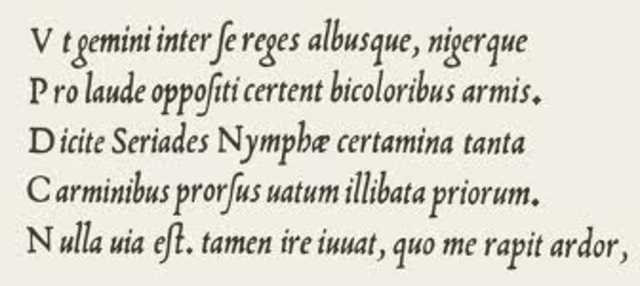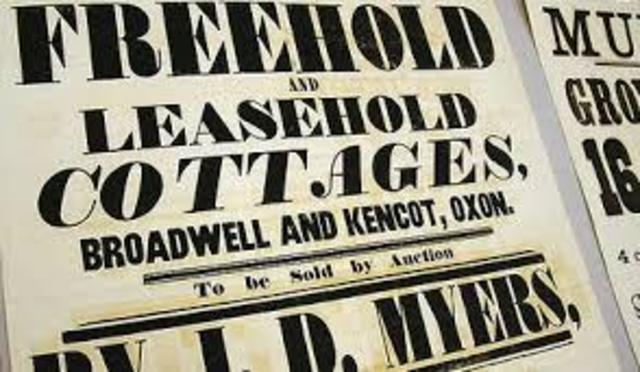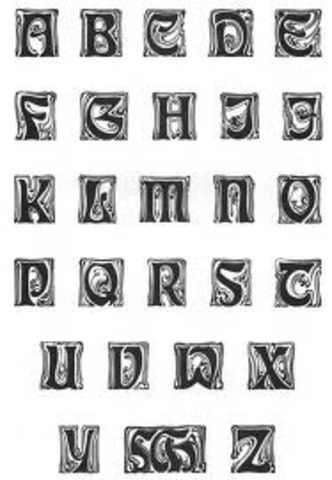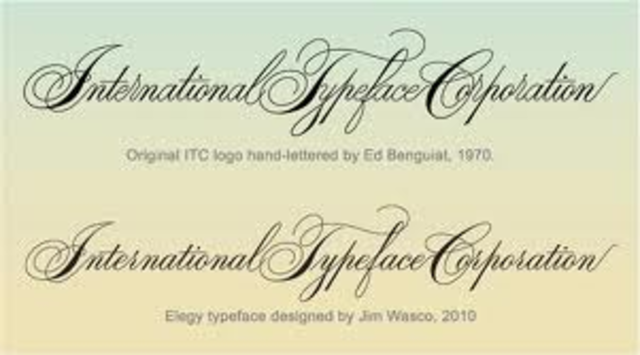
Johann Gensfleish Zum.
Desarrollo una tecnica para la elaboracion de diferentes moldes que se utilizarian para imprimir letras individuales.
Lugar: Alemania -
Introdujo la imprenta en Lyon, Francia.
imprimió el libro Le Mirover de la Rèdemption, utilizando tipos y grabados en madera importados de Basilea. -
Creó el primer manual de escritura del s. xvi; en donde publicó un segundo manual realiza do con bloques de madera, cuyas páginas estaban impre sas con tipos itá licos que él diseñó.
Fue el primer fundidor de tipos que trabajó de
forma independiente; gracias a sus caracteres romanos, los impresores franceses publicaron libros con gran legibilidad y belleza. -
Se hacen populares los libros de bolsillos. Y tambien fueron escritos libros en ingles.
inició la estandarización del tamaño de los tipos al publicar su Primera Tabla de Proporciones y abrió su propia fundición en París en 1739 y publicó su libro de modelos llamado Modèles des caractéres de l´imprimerie et desautres choses nécessaires au dit art, donde muestra sus 4600 caracteres que diseñó y talló en seis años. Dio a los impresores del Rococó un sistema completo de diseño (romanas, itálicas, plumilla, estilo decorativo, líneas y ornamentos) con medidas estandarizas.
Joseph Jackson y Thomas Cottrell:
in novadores: Joseph Jackson y Thomas Cottrell fueron prolífi cos diseñadores de letras y fundidores. Al parecer Cottrell comenzó a fundir en moldes de arena toscas letras negritas. Otros fundidores adoptaron la idea de letras más grandes y gruesas y, gradualmente, los tipos se hicieron más pesados. -
Se realizó en 2 espesores distintos y el recuerdo de la plumilla medieval se ve refl ejado en los rasgos principales de las letras, no es recomendable para cuerpos de texto.
Hermann Zapf:
Comenzo a desplazar a los caracteres de metal fundido. Lo más sobresaliente de este periodo fue la consolidación del dominio del estilo internacional suizo en el mundo de la composición; el estilo internacional de la escuela suiza se basa en el uso de una retícula para los diseños, en el uso casi excluyente de los tipos grotescos y en las composiciones asimétricas. -
Durante estos años los ordenadores ofrecieron sistemas programados para seleccionar y editar información, en combinación con componedoras que podían reproducir la imagen en una pantalla de rayos catódicos (crt) como referencia.
Fundada por Herb Lubalin y Aaron Burns, que se unieron con Ed Rondthaler, de Photo-Lettering Inc, para formar una compañía que comercializara nuevos diseños tipográfi cos. ITC lanzó su biblioteca